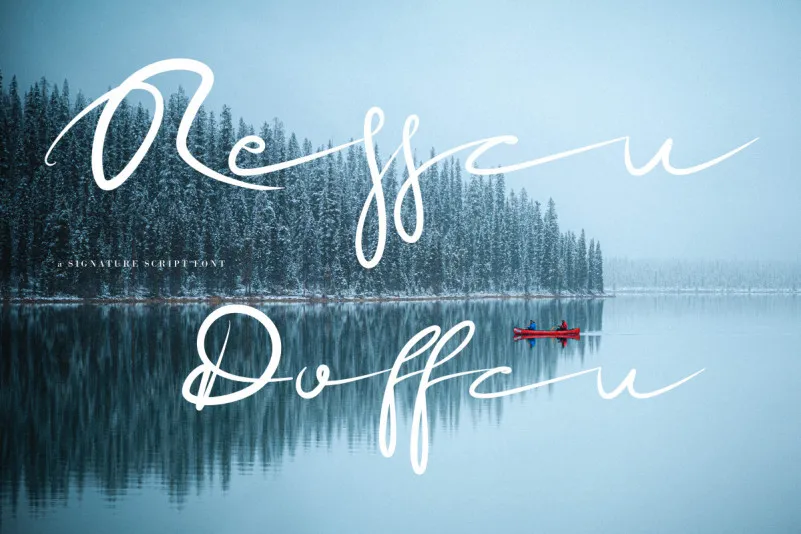
ResscuDoffcu Handwritten Font – Download Grátis
Introduzimos a ResscuDoffcu Handwritten Script Font, uma tipografia ao estilo de assinatura que transmite elegância sem esforço. Inspirada no formato de um autêntico selo, este tipo não só é simples e minimalista, mas também mantém sua essência encantadora em cada linha. A ResscuDoffcu Signature Script Font é perfeita para uma variedade de aplicativos, desde cartões de convite de casamento até logos e marcas. Suas linhas fluidas e delicadas são ideais para criações que requerem um toque sofisticado e elegante, tornando-a uma opção ideal para designers gráficos, webmasters, criadores de logomarcas ou qualquer pessoa buscando um touch único em suas criações.